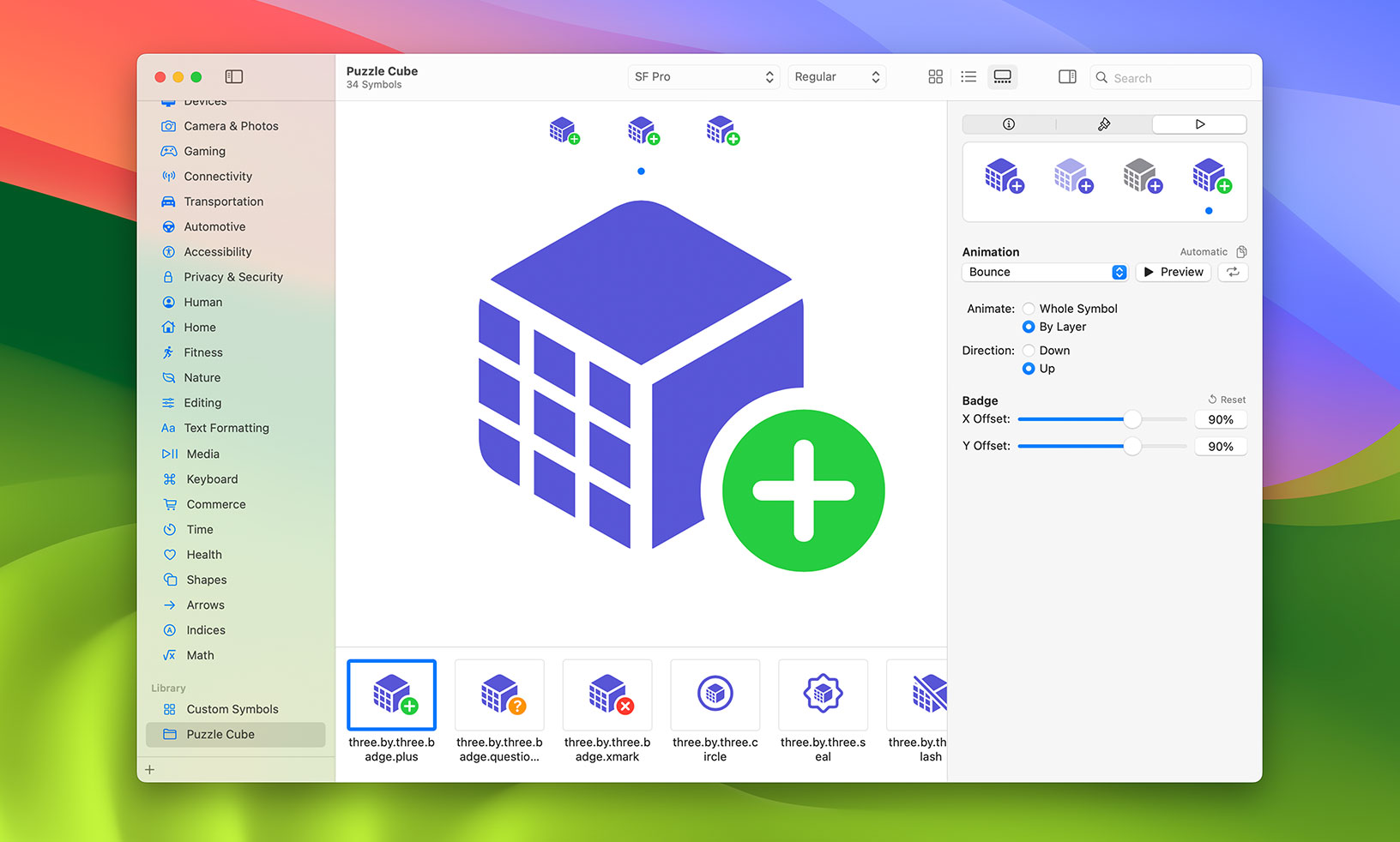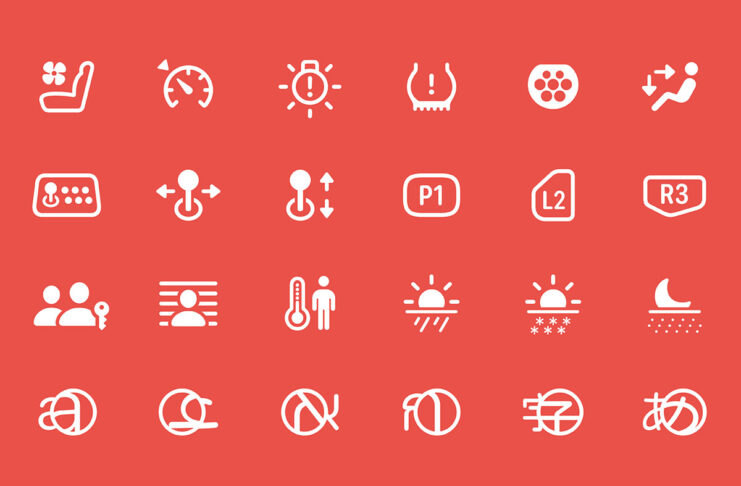
Apple ha aggiornato il font SF Symbols
Apple ha presentato SF Symbols 5, nuova versione di un font pensato per sviluppatori e che include nuove centinaia di nuove icone utilizzabili all’interno di app.
Questo font consiste in una libreria con migliaia di simboli vari che gli sviluppatori possono usare nei loro progetti. Oltre a 700 nuove icone, SF Symbols 5 vanta peculiarità quali la possibilità di personalizzare i colori, e varie funzionalitài per l’accessibilità e la personalizzazione dei simboli.
SF Symbols è pensato per integrarsi perfettamente con la famiglia di font San Francisco, il carattere di sistema per la progettazione di software per piattaforme Apple.
SF Symbols offre oltre 5000 simboli, inclusi pittogrammi quali gamepad, altri dedicate alle condizioni meteorologiche, simboli di valute, indicatori usati negli autoveicoli e molti altri ancora, incluse varianti per lingua araba, cinese, ebraico, giapponese, coreano, ecc. Questi simboli sono disponibili per app eseguite su iOS 17, iPadOS 17, macOS Sonoma, tvOS 17 e watchOS 10.
SF Symbols 5 include simboli che è possibile sfruttare per animazioni nelle app con effetti quali rimbalzi, ridimensionamento e impulsi, movimenti che appaiono secondo il layer selezionato. Apple spiega che gli effetti animati permettono di “portare vitalità alle interfacce e fornire feedback all’input utente per comunicare cambiamenti di stato nell’attività in corso”.